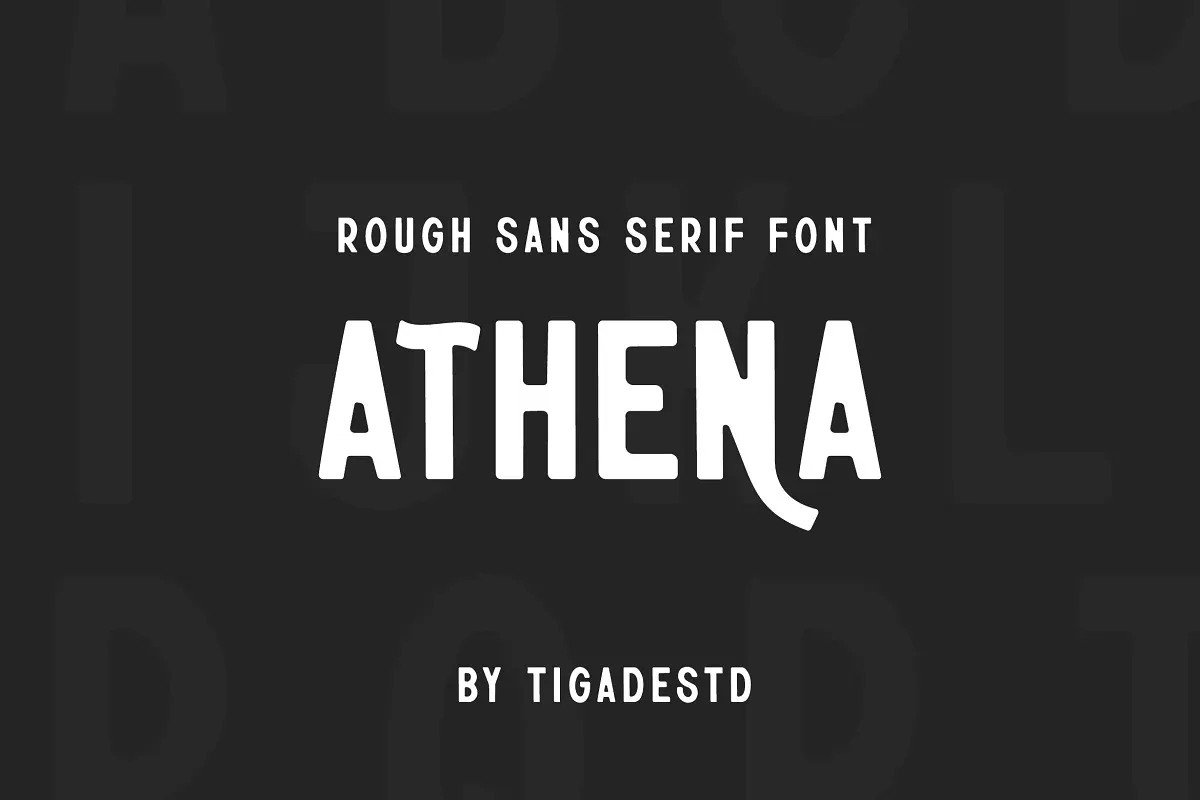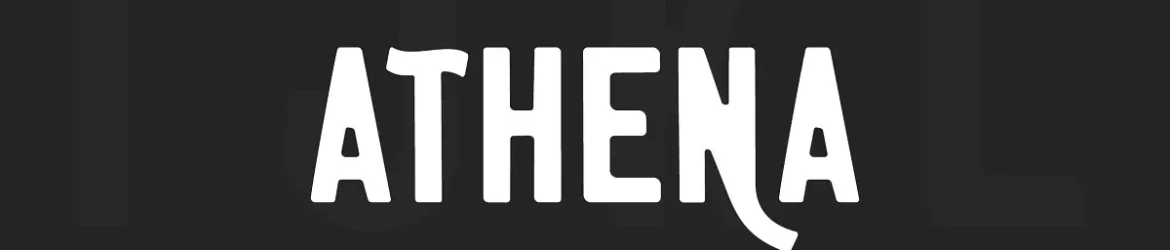
A Athena Font é uma escolha irresistível para aqueles que procuram uma mistura moderna e retrô na sua identidade visual. Desenvolvida pela Tigadestd Type, essa fonte de tipo aberto oferece um estilo único combinando elementos de exibição modernos com um toque nostálgico. Inspirada em desenhos à mão sobre papel, a Athena captura o espírito autêntico e natural de cada caractere, criando uma experiência única que remete aos tempos antigos enquanto permanece atual e inovadora. Em seu modo moderno e condensado, ela traz um ar sofisticado para qualquer projeto, enquanto em suas versões mais românticas lembra a simplicidade de desenhar em papel, proporcionando uma conexão nostálgica naturalmente. Ideal tanto para marcas quanto para textos interiores, a Athena é perfeita para designers buscando equilibrar as tendências modernas com elementos vintage.